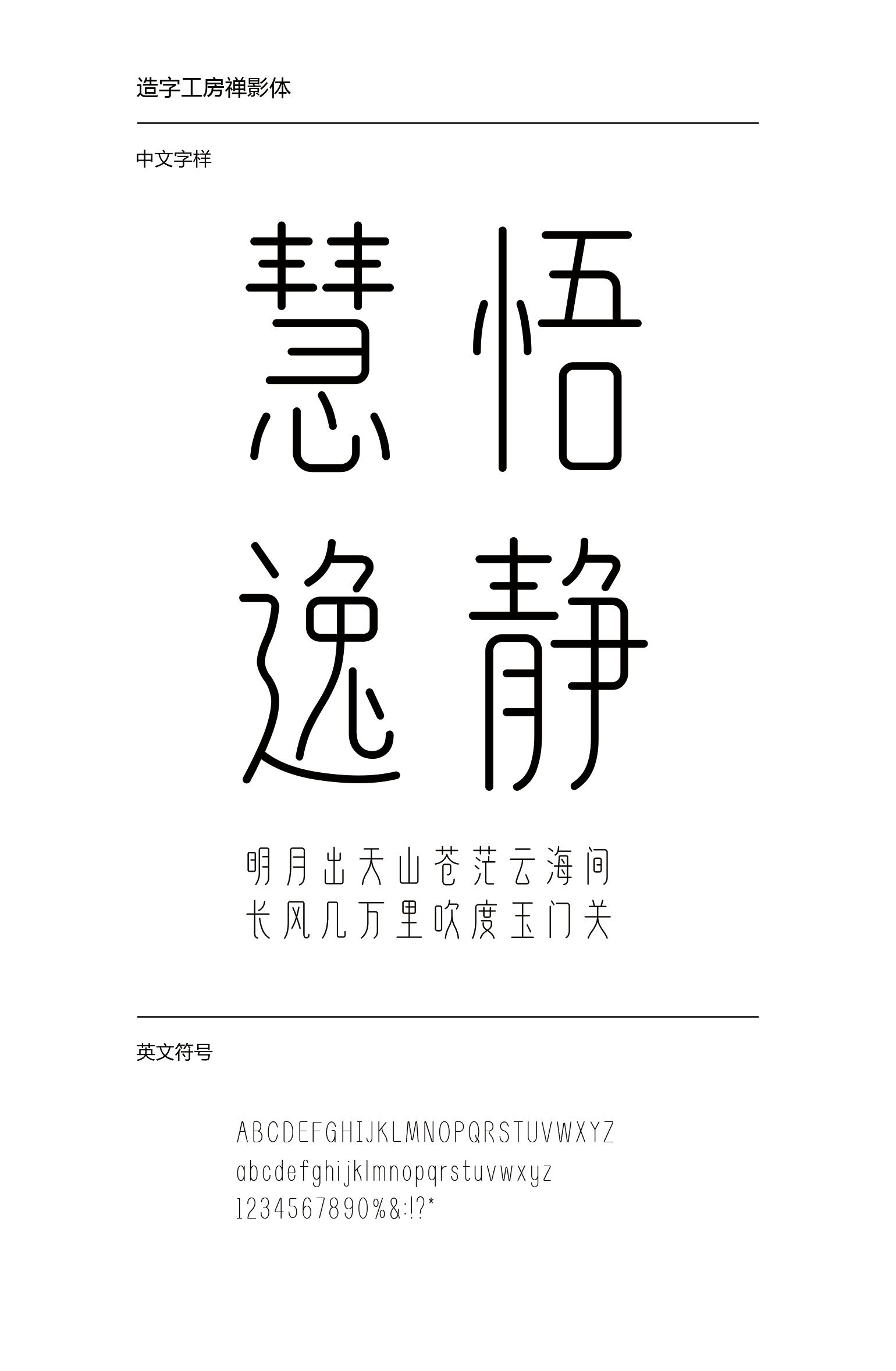
造字工房禅影体
造字工房禅影体设计说明
造字工房禅影体体势修长、笔画停匀,体态端庄而妍美,结体疏松古拙又不失端庄雅正之感。适用于大标题及个性品牌设计推广等环境。本字体为简体字库,采用OpenType/CID格式,Adobe-GB1-5编码。基于中华人民共和国GB2312-80字符集标准,另按需添加101个汉字。共收容字数6864CJK汉字,ASCII常用字符100个。